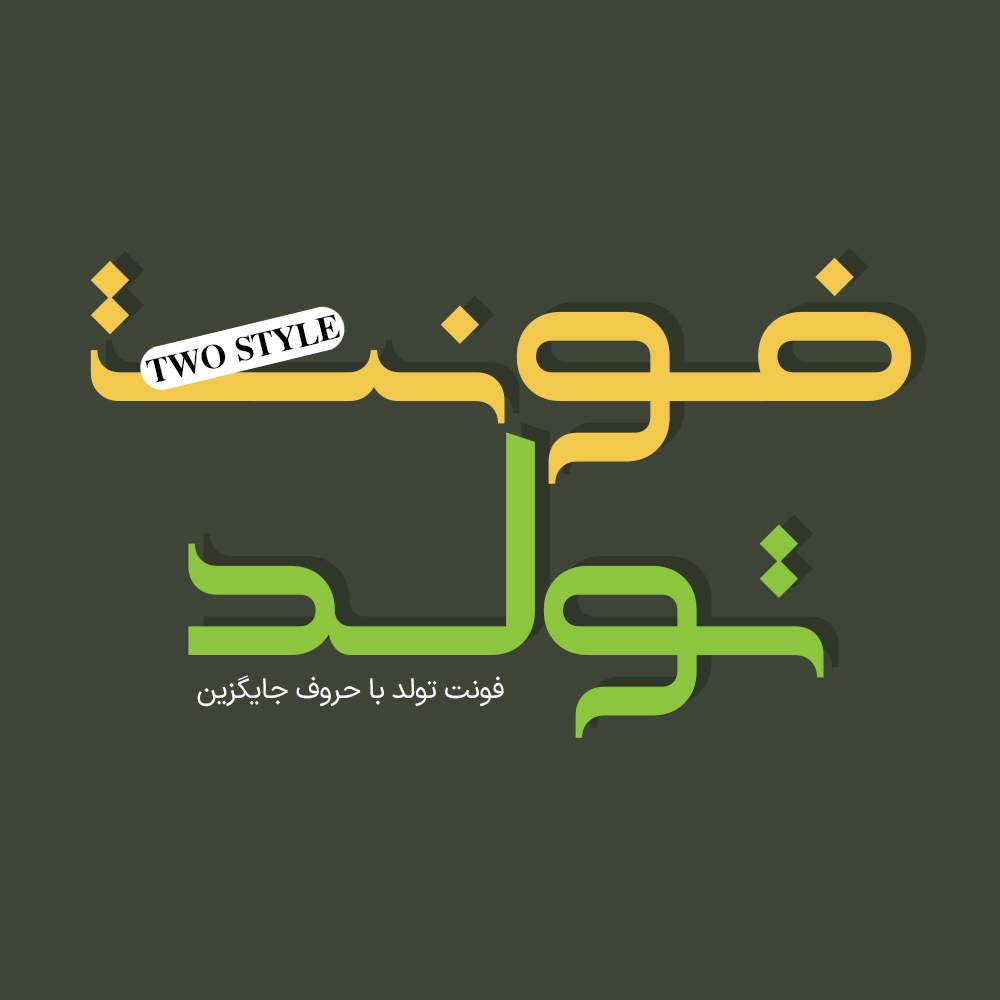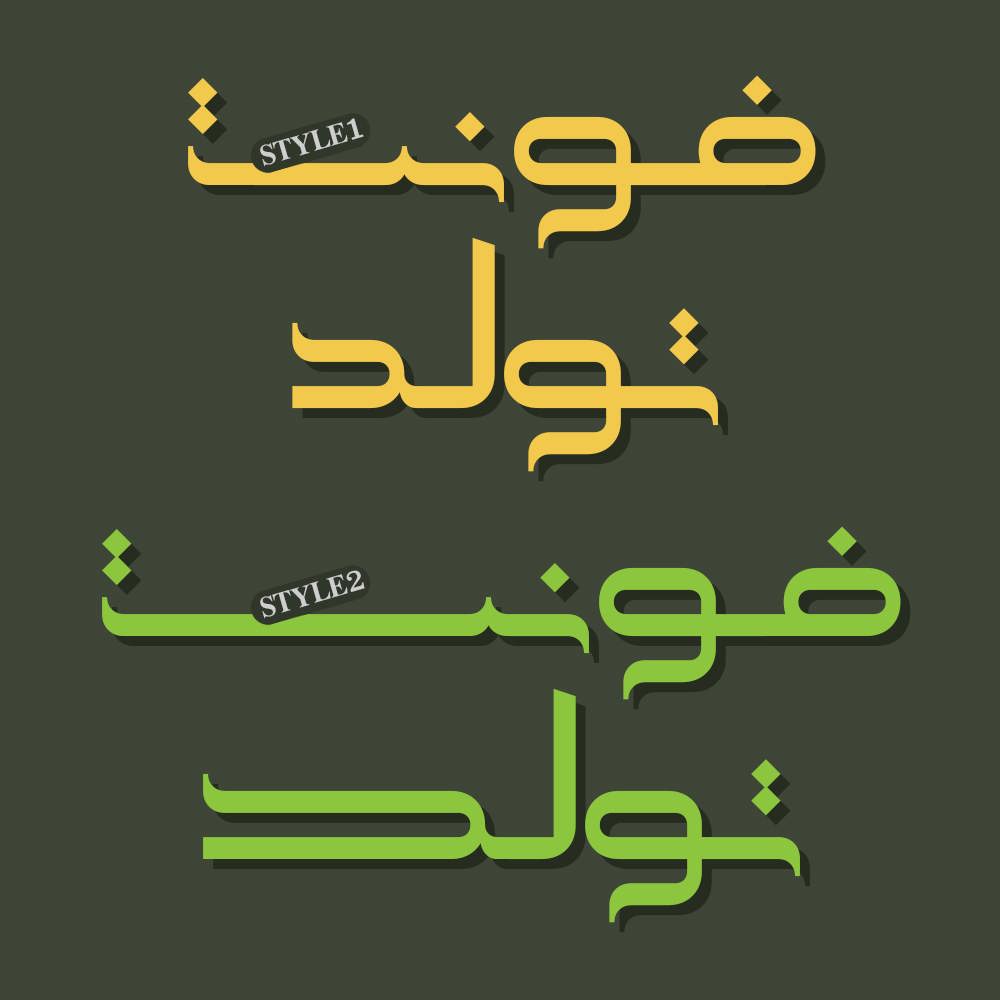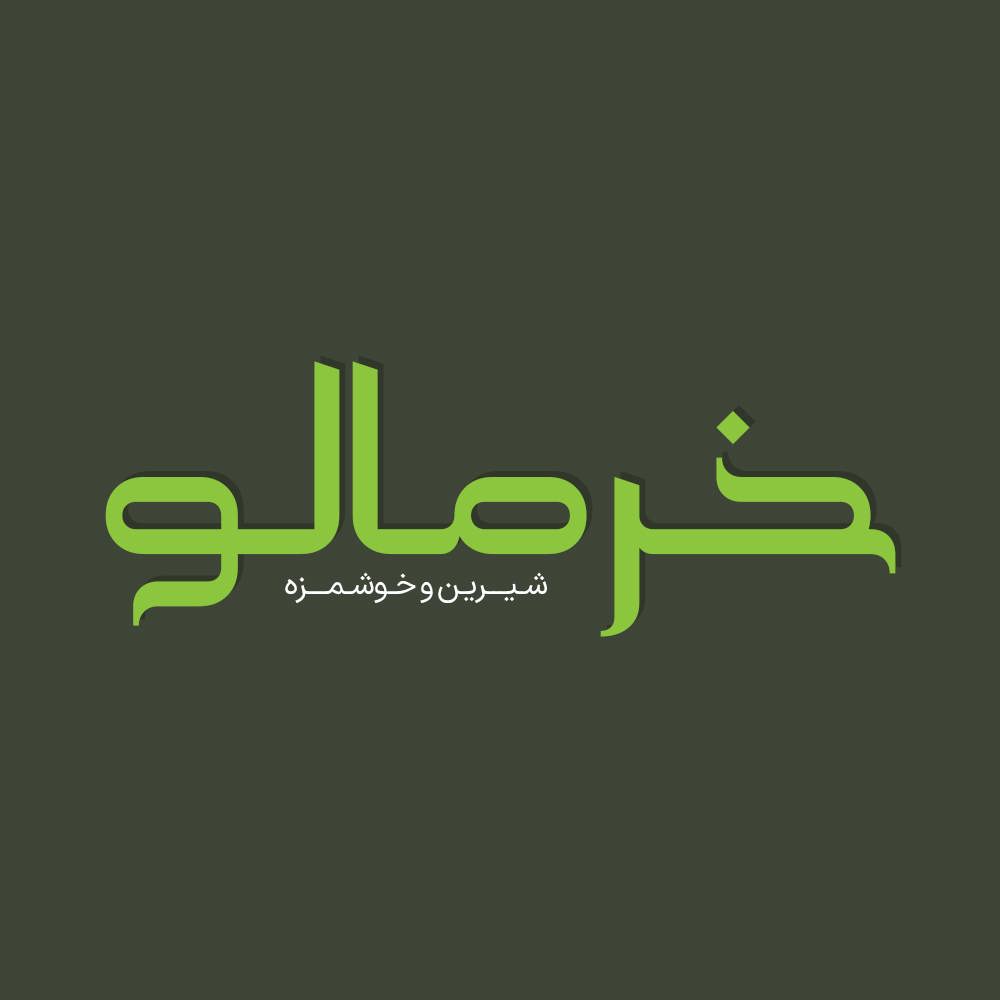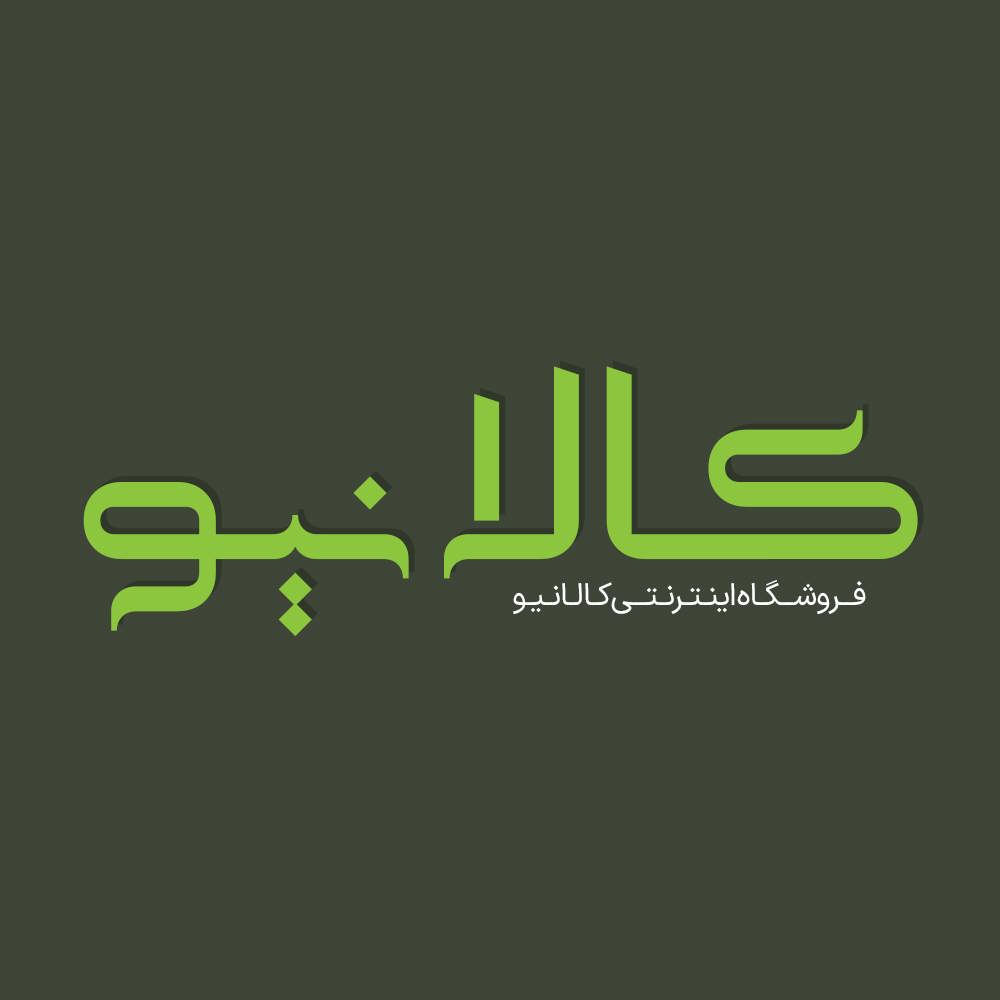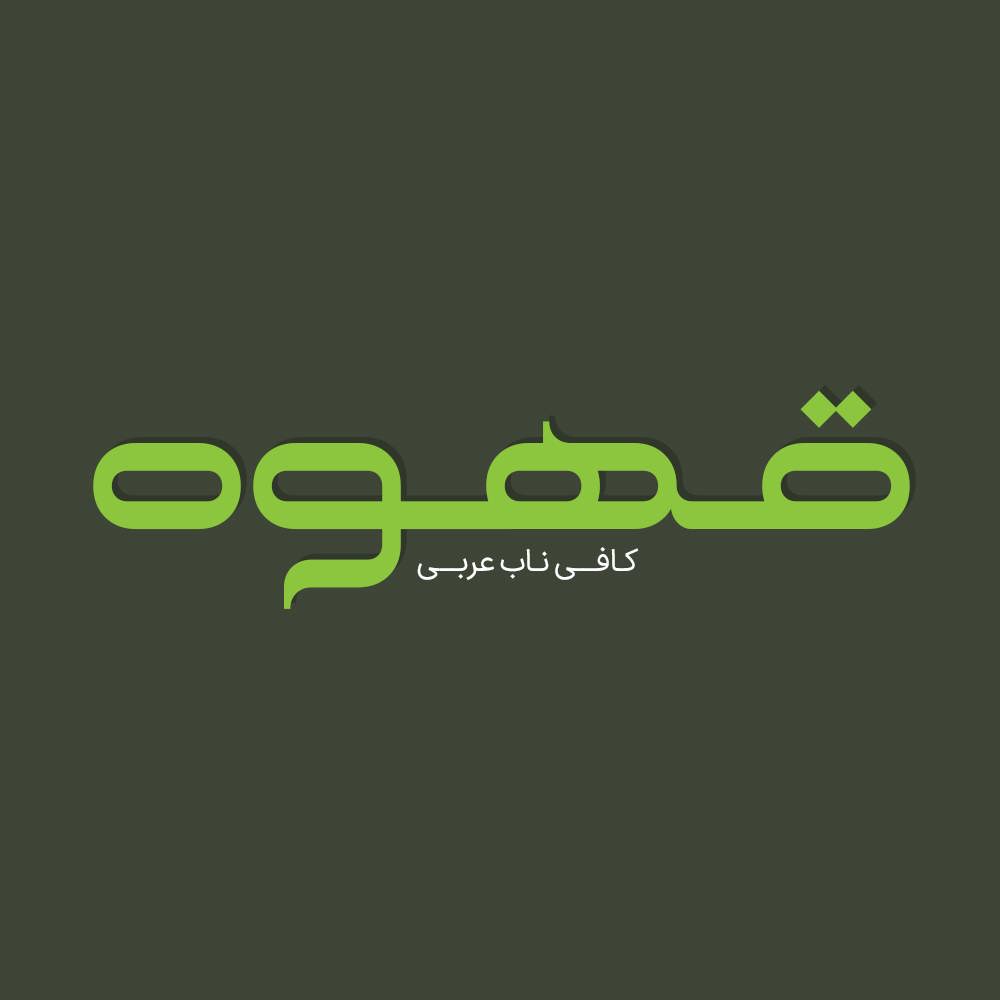
فونت فارسی تولد Tavalod Font
فونت تولد از لیگچرها (حروف ترکیبی) و آلترناتیوها (حروف جایگزین) پشتیبانی میکند. این به این معنی است که فونت تولد دارای حروف کشیده، جایگزین و حروف ترکیبی دو کاراکتری است و با استفاده از این امکانات جذاب میتوانید حروف را با حالتهای مختلف نمایش داده و نسخههای متفاوتی را انتخاب کنید.
فونت فارسی تولد شخصیتی چندگانه دارد که به آن جذابیت و استحکام میبخشد. فونت تولد یک فونت تک وزن با کاربرد طراحی لوگوتایپ و طراحی های مختلف همچون کتاب و تولید محتوای متن های کوتاه و عناوین می باشد. این فونت با فرمهای سخت و نرم خود مناسب استفاده در لوگوهای نوشتاری می باشد. همچنین از این فونت در طراحی تابلوهای چلنیوم هم به دلیل ساختار منحصر به فردش می توانید استفاده کنید. در ادامه برای شما نمونه تایپ های این محصول حرفه ای رو آماده کردیم که میتونید مشاهده کنید.
پیشنمایش و نمونه تایپ های فونت تولد